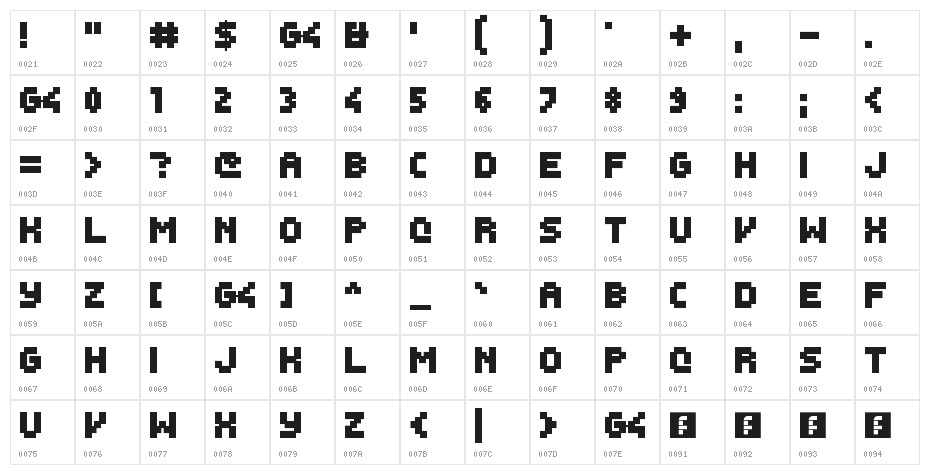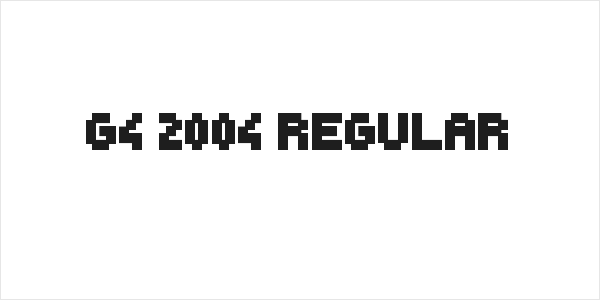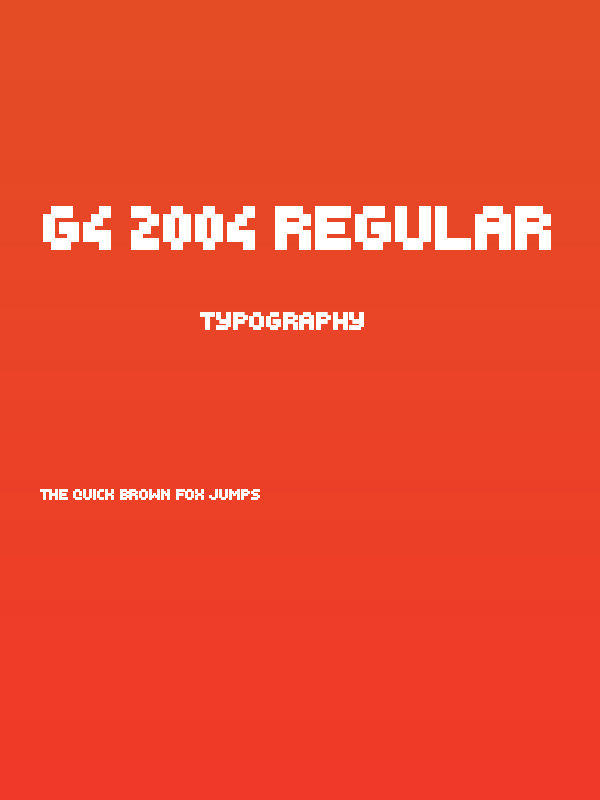
G4 2004 Regular Font
| Categorie | Pixel |
| Stile generale | Retro, Digital |
| Caso d'uso | Headlines, Logos, Digital Art |
| Progetti proposti | Ideal for retro-themed video games, digital art projects, tech-related branding, and nostalgic graphic designs. |